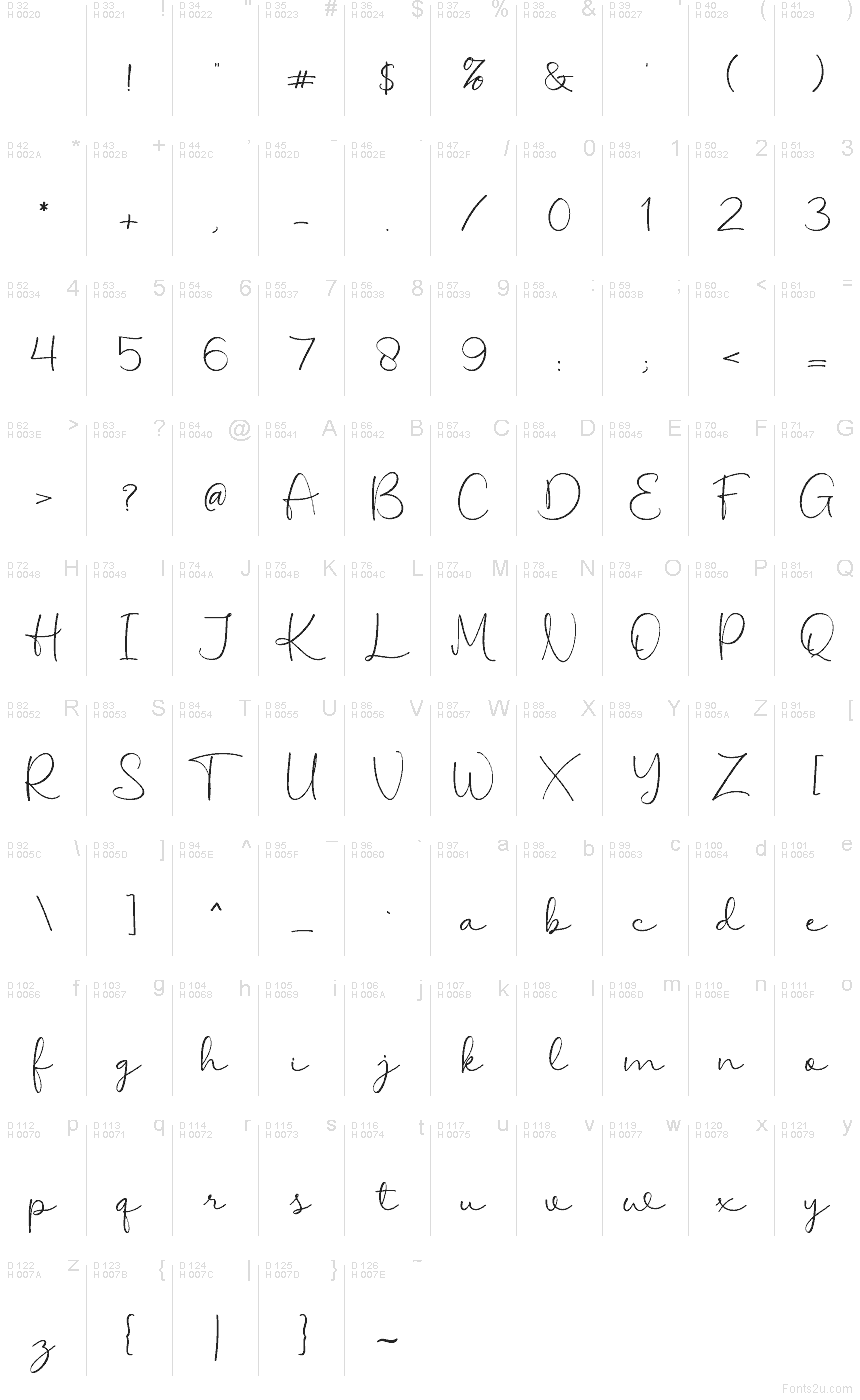
Timeless Wonderland di Rinaldo Hasibuan del Letterhanna Studio è un font calligrafico gratuito dal tocco leggero e arioso, come se fosse stato scritto con un pennarello a punta fine su carta liscia. I tratti alti e dinamici e le lunghe linee trasversali gli conferiscono un ritmo da libro di fiabe, mentre la spaziatura ampia lo mantiene leggero e pulito.
Timeless Wonderland è perfetto per partecipazioni di matrimonio, citazioni romantiche, loghi per boutique, packaging nel settore beauty, biglietti d'auguri, post sui social media e intestazioni di blog. Impostalo con una dimensione leggermente più grande per far risaltare la delicatezza dei tratti e abbinalo a un sans serif discreto, come Montserrat o Poppins, per il testo principale: questo font gratuito ci mette il fascino, il sans serif fa il lavoro.
Timeless Wonderland
Timeless Wonderland is a captivating calligraphic handwritten script font that weaves a story of timeless beauty and enchantment. Each stroke of this font is a testament to the artistry of calligraphy, making it the perfect choice for creative projects that seek to blend elegance with an enduring sense of wonder.